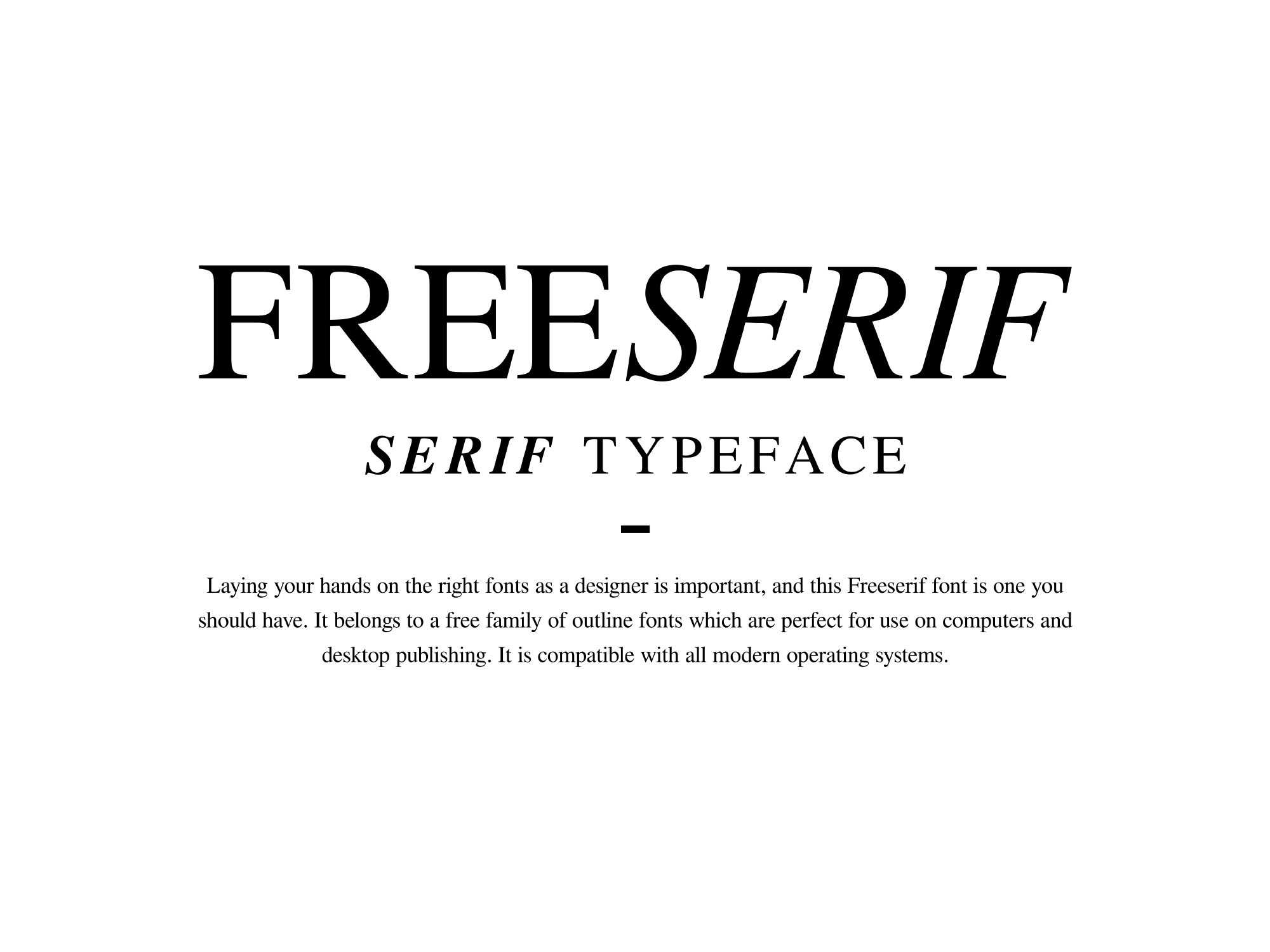
Free Serif Font Family
Sua necessidade de uma fonte Serif livre para projetos de design gráfico, ou para identificar uma marca, se torna muito mais fácil com a FreeSerif. Esta fonte pertence a uma famíliade de fontes sem contorno gratuitas, ideais para a criação de gráficos e para projetos de impressão de escritório. Com compatibilidade com todas as operações modernas, a FreeSerif é a escolha perfeita para quem busca uma fonte de qualidade sem ter que gastar um centavo. Além disso, oferece uma variedade de caracteres únicos que são baseados tanto na alfabética latina quanto em símbolos, garantindo que você tenha tudo o que precisa para personalizar seu design. Não importa o projeto que você esteja trabalhando, a FreeSerif é uma fonte que atende a todos os requisitos.